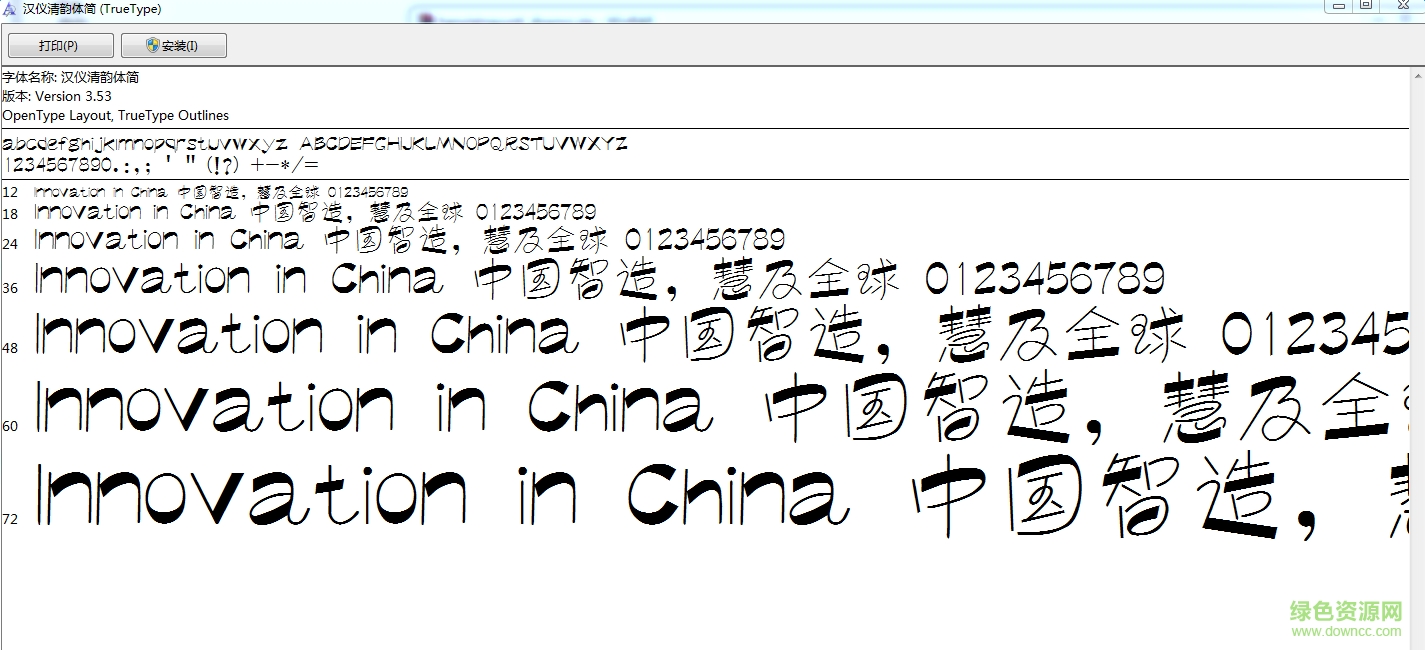
hyg4gj
hyg4gj(漢儀清韻體簡)是一款清新脫俗的漢儀字體,字體優(yōu)雅,筆畫單純,線條柔和,字形清晰美觀,閱讀效果良好,喜歡的朋友快來綠色資源網(wǎng)下載吧!
hyg4gj字體介紹
漢儀清韻體簡是一款非常不錯的電腦字體,,本作品可用于廣告設計字體、網(wǎng)頁設計字體、包裝設計字體、 屏幕顯示字體等